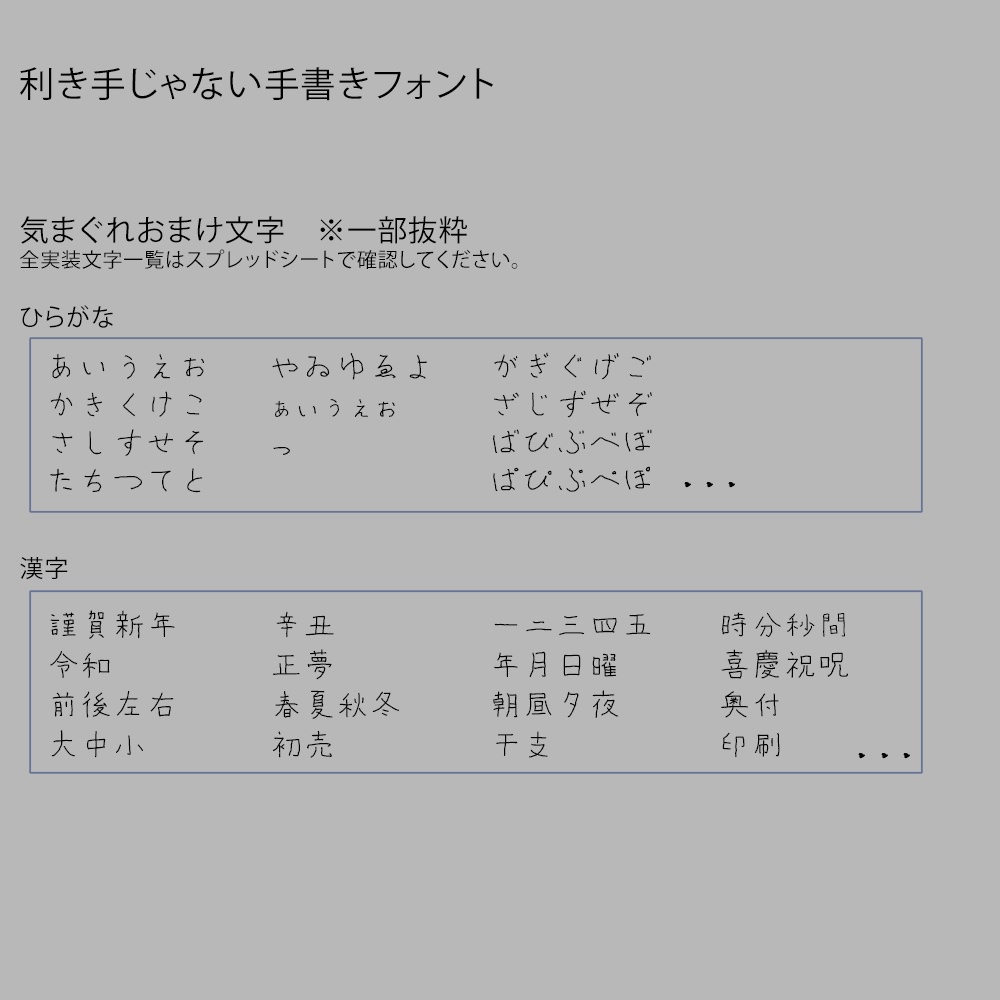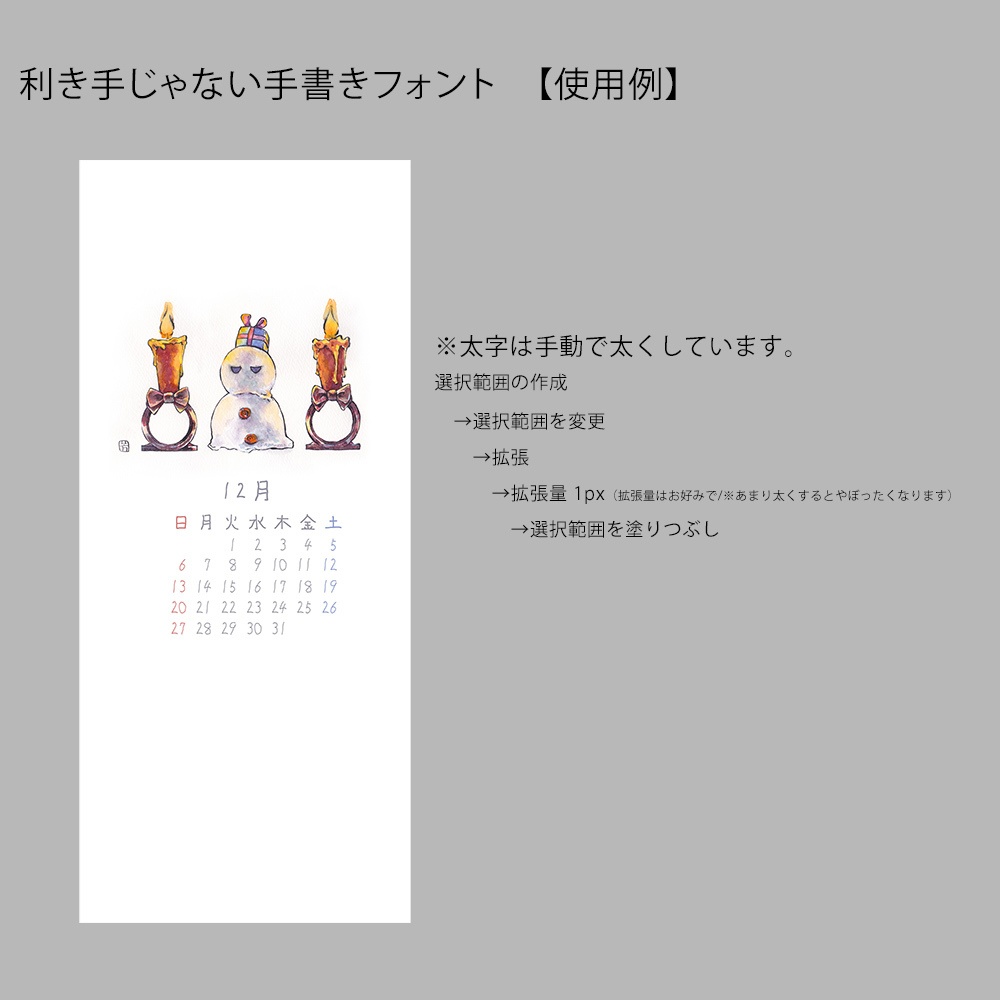
【商用可】利き手じゃない手書きフォント
■基本収録文字 ・数字(全角・半角) ・英字(全角・半角) ・よく使う(と思っている)記号(全角・半角) ・ひらがな ※サンプル版にひらがなを入れたので、基本収録文字扱いにしました。 ■不定期で追加されるかもしれない【気まぐれおまけ文字】 ・カタカナ ・漢字 ・他 収録文字リストはコチラから確認できます。 https://bit.ly/347NW8c
このフォントについて